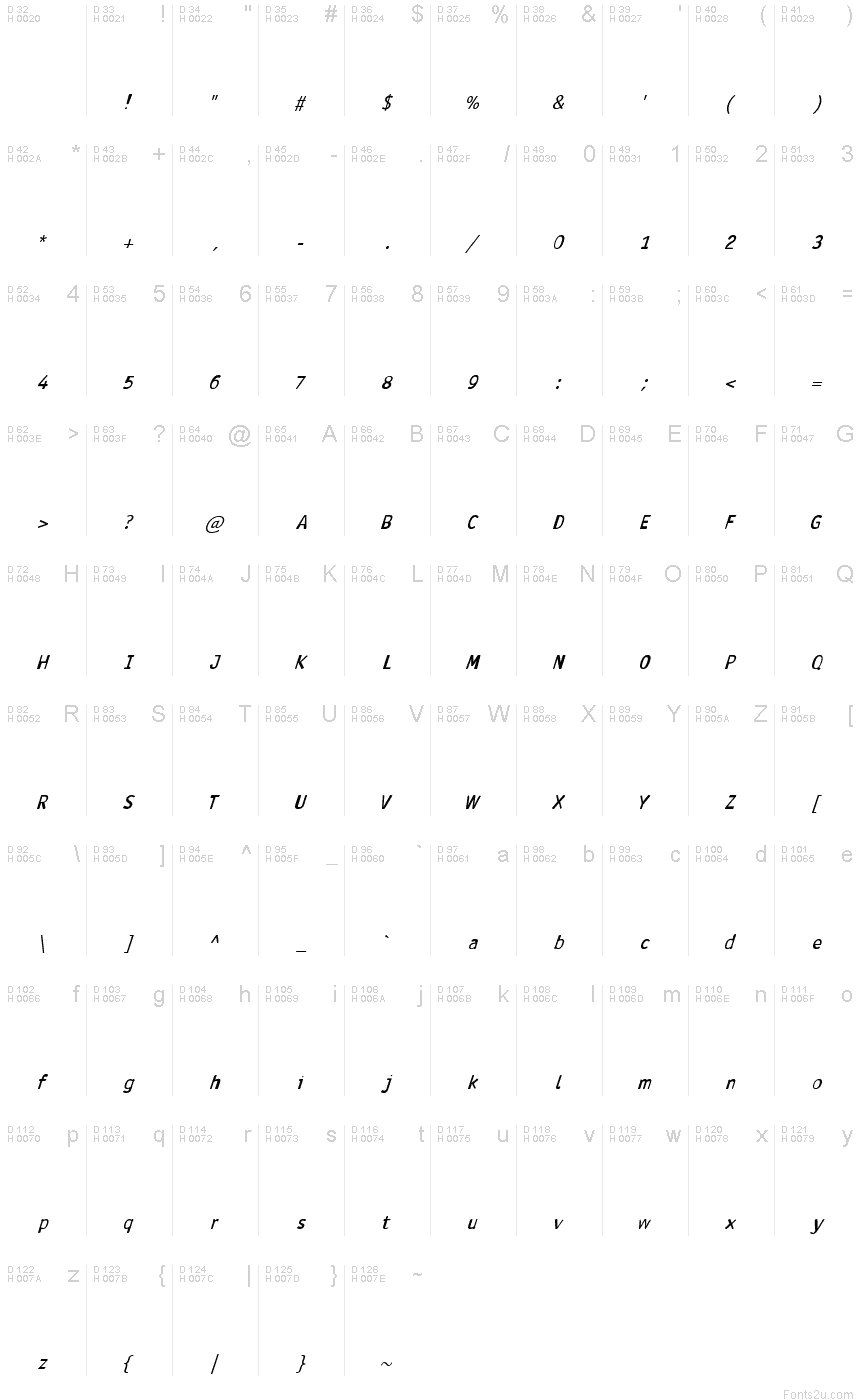
خط Antaviana Bold Italic من تصميم Josep Patau في Bellart، هو خط عرض (Display) عصري ومجاني يتميز بإيقاع حيوي وانسيابي. تميل الحروف إلى الأمام بثقة في حركة مائلة، مع ضربات سميكة تشبه الحبر تمنح شعوراً بالرسم اليدوي الذي خضع لتعديل دقيق. تتمتع المنحنيات بحيوية ملموسة، بحيث تبدو حتى الكلمة الواحدة وكأنها في حالة حركة، مما يجذب الانتباه دون أن يبدو التصميم فوضوياً أو مزخرفاً بشكل مبالغ فيه.
باستخدام Antaviana Bold Italic، ستكتسب العناوين وشعارات الكلمات على الفور شعوراً بالحركة والشخصية التي يصعب تزييفها. هذا الخط المجاني يتألق على أغلفة الكتب، وعناوين الأفلام، وعلامات البوتيك التجارية، والملصقات، والتغليف، ورسومات وسائل التواصل الاجتماعي الجريئة حيث تريد لاسم قوي أن يقود التصميم. استخدمه مع خط "سان سيريف" هندسي نظيف للنصوص الصغيرة، ودع Antaviana يتولى المهمة في اللحظات الكبيرة والدرامية بأحجام أكبر.
خريطة محارف خط Antaviana BoldItalic